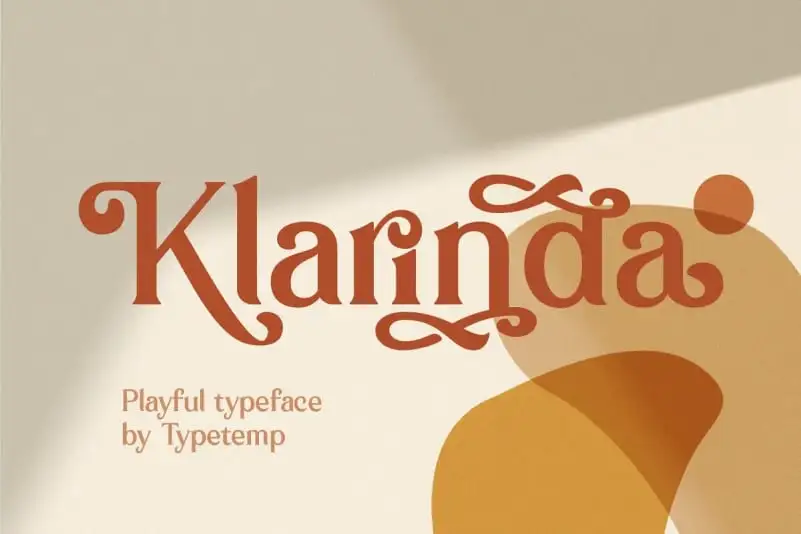
A Klarinda Serif é uma escolha perfeita para aqueles que procuram um tipo serif moderno com swashes. Desenvolvida pela Typetemp Studio na plataforma 99designs, esta fonte oferece alternativas estilísticas e ligaturas que a tornam ainda mais única. Ela não se mistura no meio do turbilhão de fontes existentes, mas sim brilha, destacando-se de uma maneira elegante e sofisticada. Com um estilo leve, ou seja, lúdico, esta fonte traz alternativas estilísticas e ligaturas que criam marcas memoráveis para logos, citações, postagens nas redes sociais, posts em blogs, projetos de marca, imagens para revistas, convites para casamentos e muito mais. Esta fonte não apenas oferece estilo, mas também uma grande versatilidade quando se trata de criar elementos visuais que chamam atenção e reforçam sua marca ou projeto.